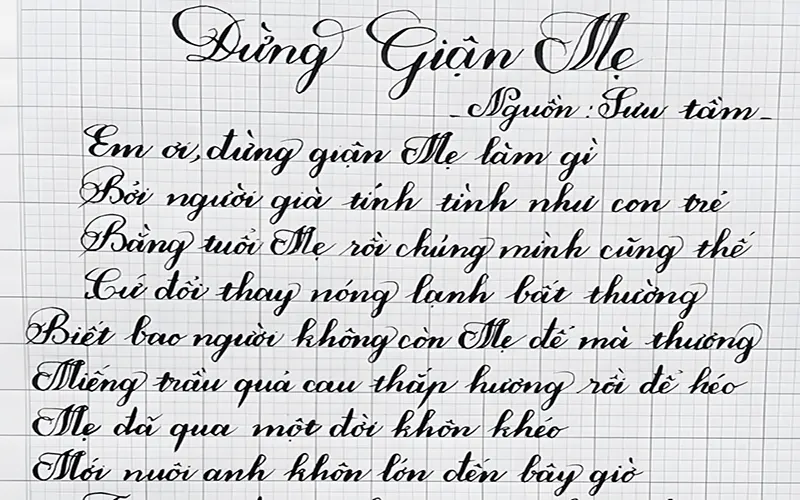
Font chữ mềm mại là font có nét cong, organic với phong cách nhẹ nhàng, nữ tính được sử dụng rộng rãi trong thiết kế bao bì mỹ phẩm, túi giấy spa và in ấn cho thương hiệu wellness. Font chữ mềm mại việt hóa với đặc điểm flowing, elegant tạo cảm giác dịu dàng, thanh lịch.
Font chữ mềm mại là gì?
Font chữ mềm mại là font có nét chữ cong, flowing, organic – ngược lại với font cứng có nét thẳng, góc vuông. Mềm mại không phải về font weight (đậm hay mảnh) mà về chất cảm – curves vs straight lines.
Đặc điểm font mềm mại:
• Nét cong nhiều: Ưu tiên đường cong thay vì nét thẳng – chữ S, C, O đặc biệt tròn trịa, flowing.
• Organic, handwritten feel: Nhiều font mềm mại lấy cảm hứng từ chữ viết tay – script, brush, calligraphy.
• Serif mềm hoặc humanist sans: Serif với chân tròn (Garamond-style) hoặc humanist sans với nét cong (Lato-style).
• Feminine, gentle: Font mềm mại thường được cảm nhận là nữ tính, nhẹ nhàng, duyên dáng.
Phân loại font mềm mại:
• Script fonts: Font viết tay liền mạch – mềm mại. Ví dụ: Dancing Script, Pacifico. Cảm giác: romantic, personal, handcrafted.
• Serif với nét cong: Old Style serif như Garamond, Crimson. Cảm giác: elegant, classic, literary.
• Humanist sans-serif: Sans với nét organic như Lato, Alegreya Sans. Cảm giác: friendly, warm, approachable.
• Display fonts với curves: Font display với nét cong đặc biệt. Ví dụ: Satisfy, Parisienne. Cảm giác: decorative, artistic.
Tại sao font mềm mại = feminine:
• Cultural association: Văn hóa liên kết curves với nữ tính, straight lines với nam tính.
• Calligraphy tradition: Chữ viết tay đẹp (copperplate, spencerian) truyền thống dạy cho phụ nữ – script = feminine.
• Gentleness perception: Nét cong = mềm mại, nhẹ nhàng vs nét thẳng = cứng rắn, mạnh mẽ.
Dancing Script
Script cursive, flowing Logo spa, wellness, thiệp mời nữ tính
Lora
Serif mềm, contemporary Bao bì mỹ phẩm, catalogue lifestyle
Crimson Text
Old Style serif, literary Brochure wellness, sách, tạp chí
EB Garamond
Classic serif, elegant curves Bao bì perfume, catalogue thời trang nữ
Pacifico
Script brush, surf style Logo beach brand, summer collection
Great Vibes
Script calligraphy, elegant Thiệp cưới, bao bì quà tặng cao cấp
Satisfy
Script brush casual Logo cafe, bakery, handmade brand
Alegreya
Serif humanist, warm Body text brochure, catalogue dễ đọc
Spectral
Serif contemporary, refined Editorial, magazine, lookbook
Cookie
Script brush vintage Nhãn sản phẩm handmade, organic
Lưu ý: Font script rất mềm mại nhưng không nên VIẾT HOA toàn bộ – script được thiết kế cho lowercase + uppercase mix.
Ứng dụng font mềm mại trong bao bì nữ tính
Font chữ mềm mại với phong cách gentle được ưa chuộng:
• Perfect cho beauty & wellness: Mỹ phẩm, spa, wellness brand muốn tạo cảm giác dịu dàng, chăm sóc, pampering – font mềm mại là ngôn ngữ hoàn hảo.
• Feminine products: Sản phẩm phụ nữ (skincare, lingerie, feminine care) dùng font mềm để tạo kết nối emotional với audience nữ.
• Romantic, emotional: Wedding, Valentine, romance-themed brand – font mềm mại tạo cảm giác lãng mạn, cảm xúc.
• Handcrafted, artisan: Script mềm gợi liên tưởng đến handmade, artisan – phù hợp organic, natural, small-batch product.
Font mềm mại xuất hiện trong nhiều sản phẩm in ấn:
• Bao bì mỹ phẩm: skincare, perfume, makeup – đặc biệt brand nữ tính, natural.
• Túi giấy spa, wellness: spa, salon, yoga studio, massage therapy.
• Bao bì sản phẩm phụ nữ: feminine hygiene, maternity, lingerie, jewelry.
• Nhãn sản phẩm handmade: soap thủ công, candle, skincare artisan.
• Thiệp cưới, thiệp mời: wedding invitation, bridal shower, baby shower.
• Menu wedding, events: menu tiệc cưới, dessert menu elegant.
• Catalogue thời trang nữ: lookbook women’s fashion, lingerie catalog.
• Brochure wellness retreat: spa resort, wellness center, yoga retreat.
• Hộp quà tặng nữ: gift box skincare, perfume set, jewelry box.
Font chữ mềm mại được viêt bằng tay
3. Script font có nên viết hoa toàn bộ không?
Không. Script được thiết kế cho lowercase + uppercase mix (như viết tay thật). Việc viết hoa toàn bộ sẽ rất khó đọc và mất hết vẻ đẹp flowing, bạn chỉ viết hoa chữ cái đầu.